タイププロジェクト、TP スカイの「フトコロ軸」調整を加えてフィットフォントサービスを拡張
スイスのタイプデザインスタジオDinamoの欧文53フォントも追加
タイププロジェクト株式会社(東京都練馬区 代表取締役社長 鈴木 功、以下タイププロジェクト)は、本日、新たにフトコロ軸を加えたフィットフォントサービスの拡張を発表いたしました。これにより、ウエイトや字幅、コントラストに加えて、フトコロ軸(字画の内部空間)の調整が可能になります。また、スイスのタイプデザインスタジオDinamo(ダイナモ)が新しくリリースした欧文フォントも追加しました。
フトコロ軸は、これまで和文フォントのファミリーで扱われたことのない書体属性で、TPスカイはウエイト、コントラスト、字幅、フトコロ軸の4つの軸をもつ初めての日本語フォントです。フトコロ軸の大きさを変えることにより、欧文によって異なるカウンターの広さと小文字の大きさに対応し、書体の表情をニュートラルからクラシックへと変化させることが可能です。
フィットフォントは、画面上のスライドバーでウエイトや字幅を調整することで最適なフォントをお選びいただけるサービスです。独自開発技術により、ウエイトやコントラスト、字幅、フトコロ軸を変更した場合でも、字画の比率が適正で常にバランスの取れた状態を保ち、ダイナミックに変化しながらもデザインの一貫性と品質保持を実現しています。フィットフォントサービスのプルダウンメニューでは、異なるフォントの漢字・仮名・欧文を組替えてご確認いただけます。
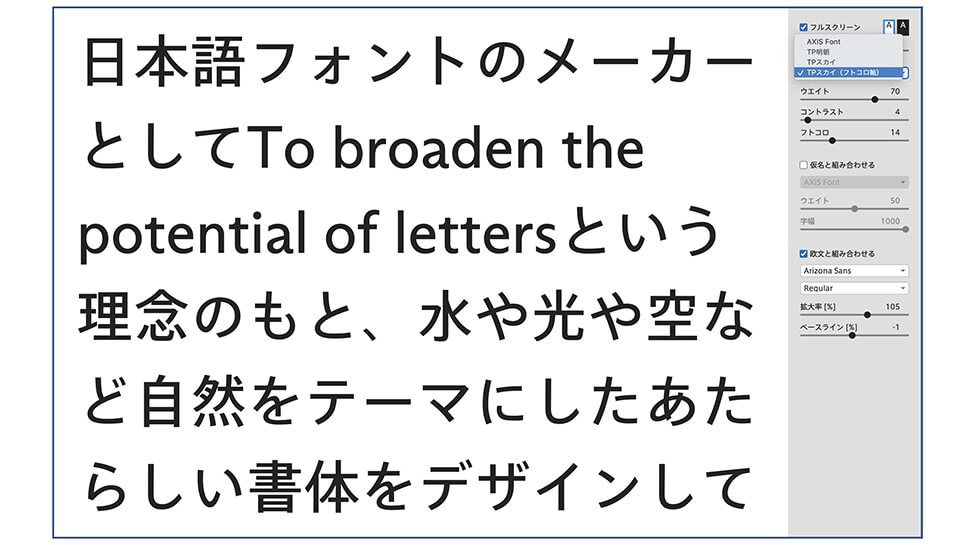
タイププロジェクトの鈴木功は、「和文フォントで扱われたことのない書体属性であるフトコロ軸の調整をフィットフォントサービスに加えること、そしてDinamo の書体の追加を合わせてお知らせできることをとても嬉しく思っています。フトコロの大きさを変えることによって変化する書体の表情をお楽しみください。今後も、国内外の欧文書体メーカーと協業することで、フィットフォントの導入が広がることを期待しています」と述べています。
Dinamoはスイスのタイプデザインスタジオで、リテールフォント、カスタムフォント、コンサルティングを提供しています。2017年にスイス文化庁が主催するSwiss Design Award(スイス・デザイン賞)を受賞し、2018年には国際グラフィック連盟の会員に推挙されています。今回、新たにフィットフォントの欧文に下記の全53書体を追加しました。
Arizona Serif (Thin/Light/Regular/Medium)
Arizona Text (Thin/Light/Regular/Medium)
Arizona Mix (Thin/Light/Regular/Medium)
Arizona Sans (Thin/Light/Regular/Medium/Bold)
Diatype (Thin/Light/Regular/Medium/Bold)
Favorit (Light/Book/Regular/Medium/Bold)
Marfa (Thin/Light/Regular/Medium/Semibold/Bold)
Social (Hairline/Thin/Light/Book/Regular/Medium/Bold)
Social Condensed (Hairline/Thin/Light/Book/Regular/Medium)
Social Extended (Hairline/Thin/Light/Book/Regular/Medium/Bold)
タイププロジェクトでは、企業のメッセージを伝えるための手段としてフォントによるブランディングを提案しています。フィットフォント技術を用いて、AXIS FontやTP明朝、TPスカイのウエイトや字幅、コントラスト、フトコロ軸を調節することで最適な組合せを提供します。欧文部を他社欧文と組替えるほか、オリジナルのひらがなやカタカナを開発するなど、世界有数のグローバル企業にコーポレートフォントを提供しています。
フィットフォントサービスでは、Dinamoの他に、Commercial Type(コマーシャルタイプ、米国 ニューヨーク)、Production Type(プロダクションタイプ、フランス パリ)、Typotheque(タイポテーク、オランダ ハーグ)、Grilli Type(グリリタイプ、スイス ルツェルン)の欧文書体との組合せもお試しいただけます。